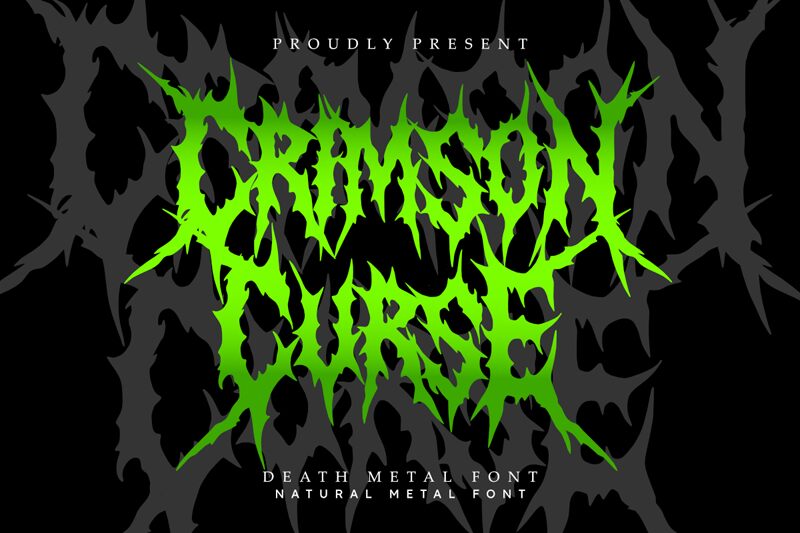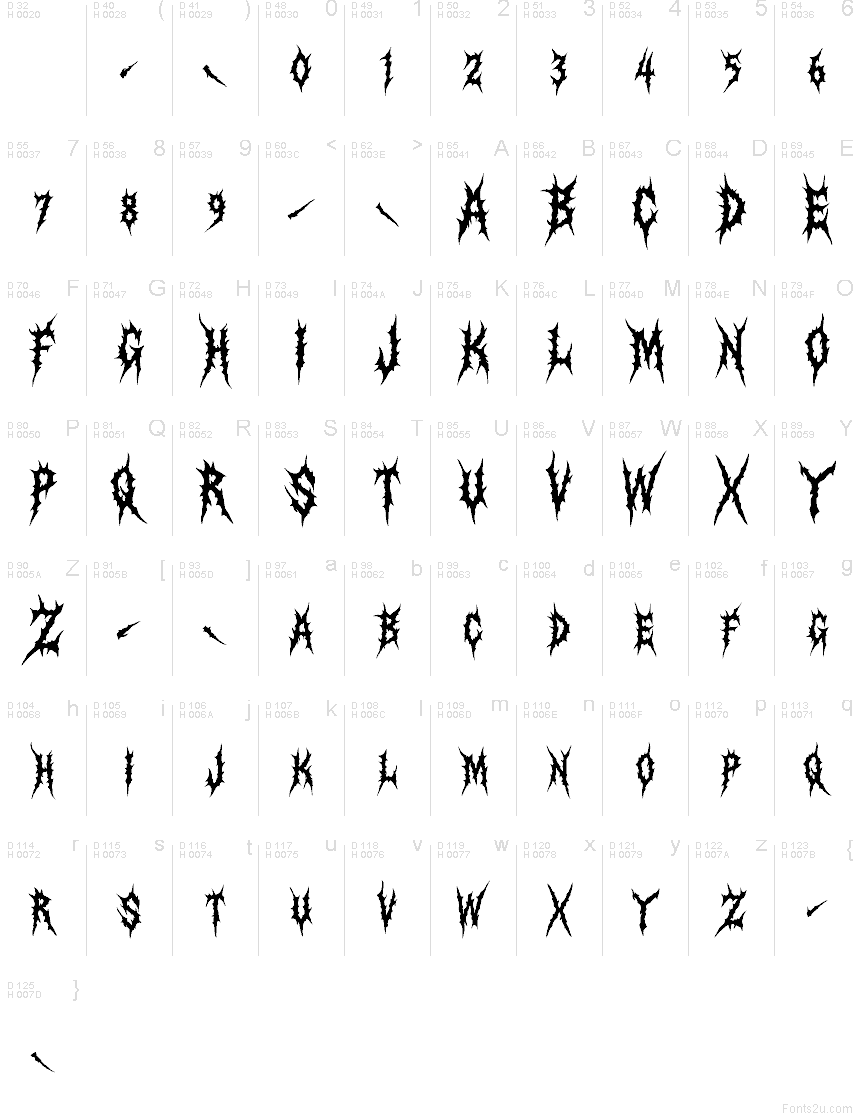
Crimson Curse Regular
La police Crimson Curse, créée par Masyafi Studio, est une typographie d'horreur gothique gratuite caractérisée par ses bords acérés et ses pointes acérées. Ses caractères se décomposent en découpes dentelées et en formes rappelant des flammes, conférant à l'ensemble une allure brute et agressive, comme si le texte avait été sculpté plutôt que dessiné.
Crimson Curse est parfaite pour les affiches de films d'horreur, les logos de groupes de métal, les titres de jeux vidéo, les flyers d'événements et les pochettes d'albums, car ses formes fragmentées distillent instantanément un sentiment de danger et de tension. Cette police gratuite convient également aux articles dérivés effrayants et aux titres décoratifs audacieux où le lettrage doit paraître abîmé et dramatique sans avoir recours à des effets supplémentaires.